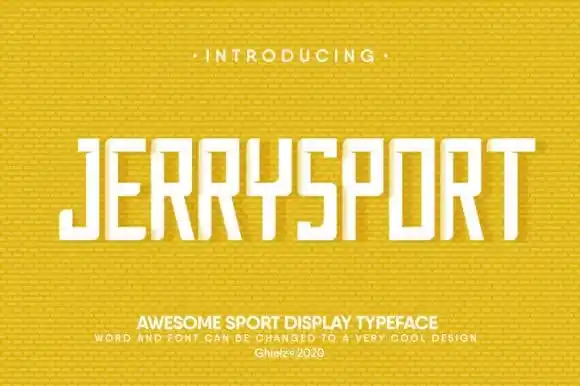
JerrySport Display Font – Download Grátis
A fonte ‘JerrySport Display Font’ é uma escolha perfeita para quem busca algo dinâmico e vibrante. Inspirada nos desenhos urbanos e no design esportivo, esta fonte all caps apresenta um aspecto retro com elementos modernos. É uma opção ideal tanto para projetos formais quanto informais. Suas linhas clean e fortes combinam perfeitamente com estilos que valorizam a informalidade urbana. O JerrySport Display Font é especialmente adequado para múltiplas aplicações, como as maquetes de vlogs, logomarcas, banners para lojas de moda ou cafés, além do marketing musical e promocional para restaurantes. Suas linhas distintivas criam um impacto visual notável em qualquer projeto, proporcionando uma identidade única que combina a modernidade com um toque de nostalgia. Adicione esta fonte à sua próxima criação e tenha certeza de apreciar o resultado final. A JerrySport Display Font é a escolha perfeita para criar designs inovadores e vibrantes, adaptando-se perfeitamente às diversas necessidades das comunicações digitais contemporâneas.